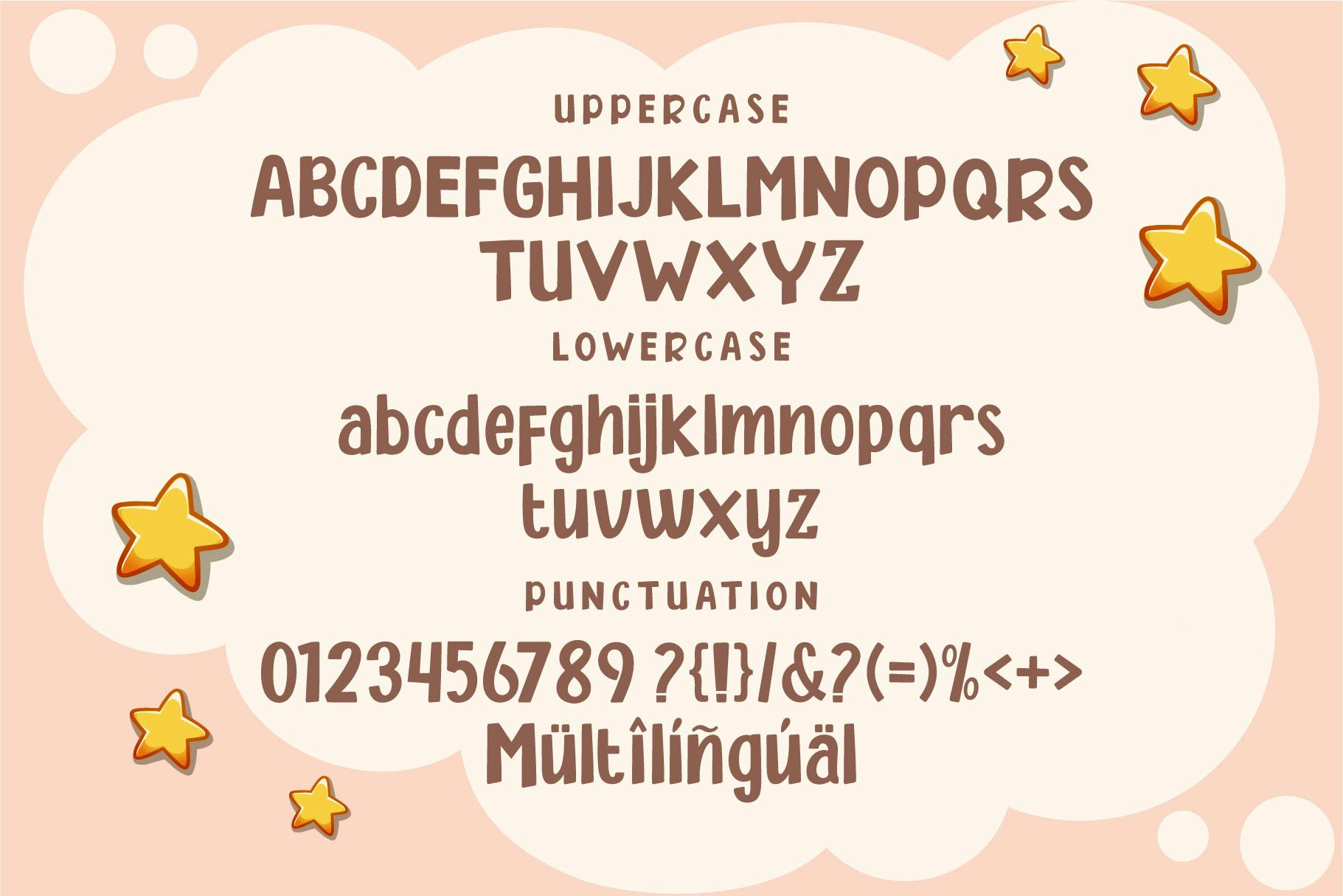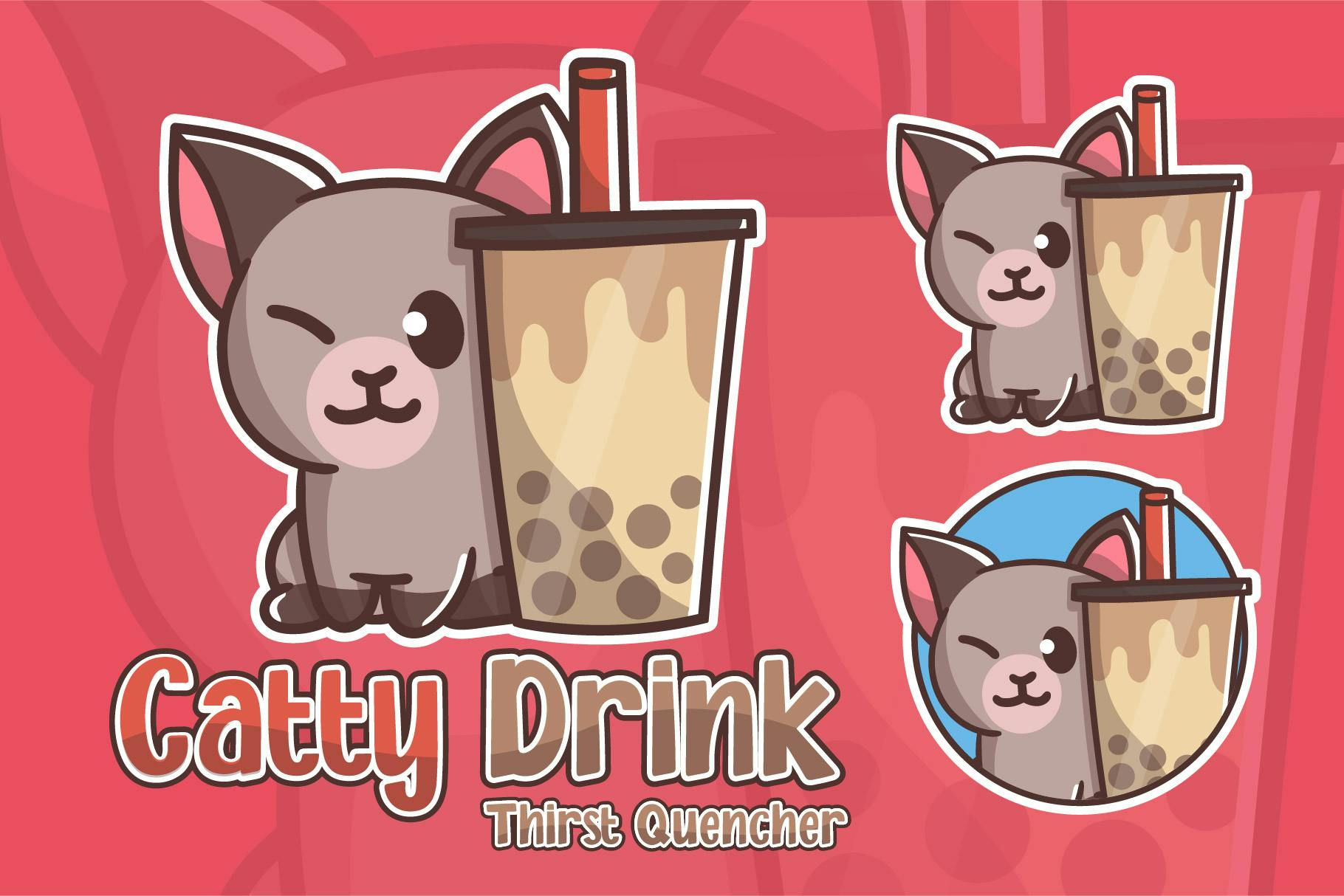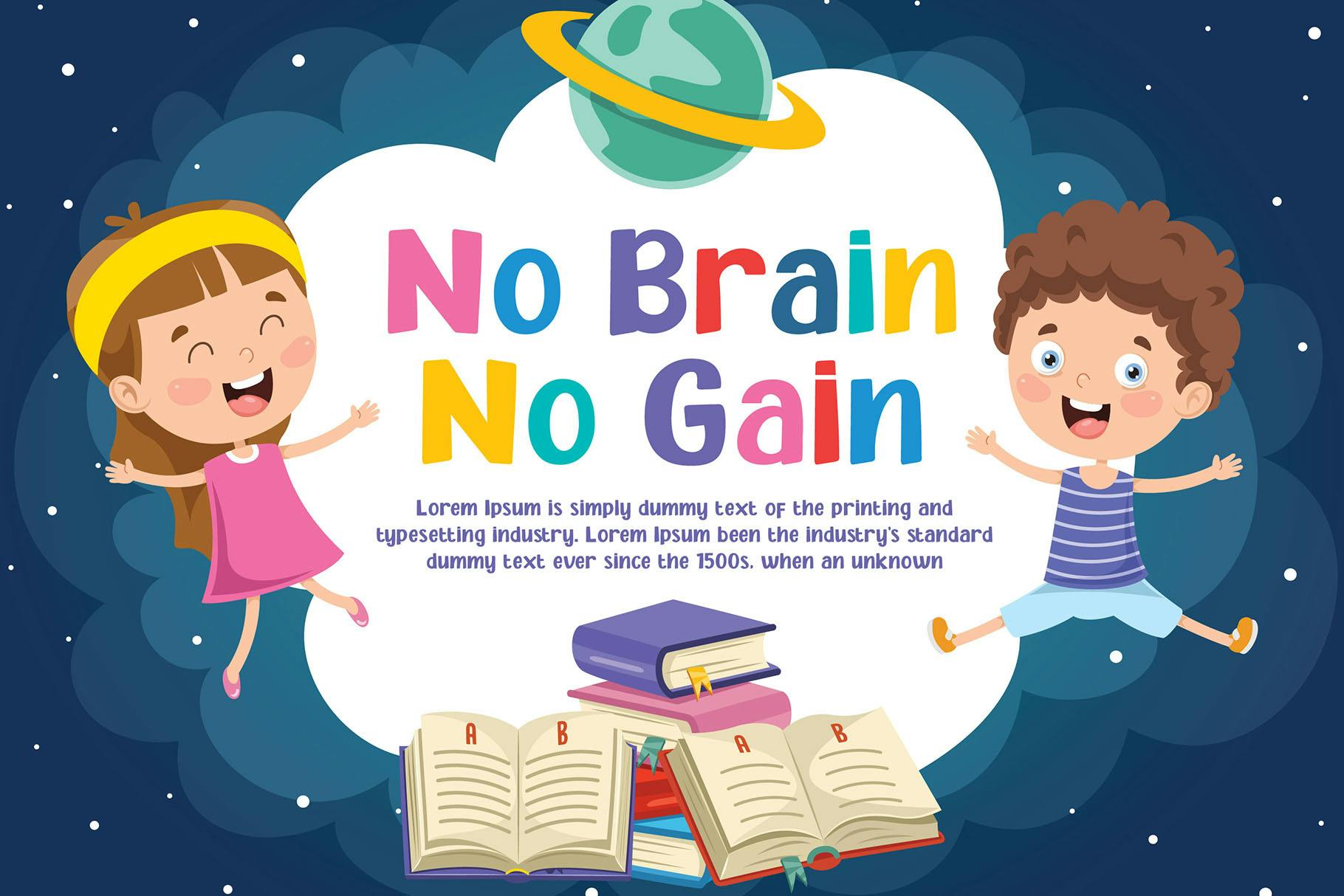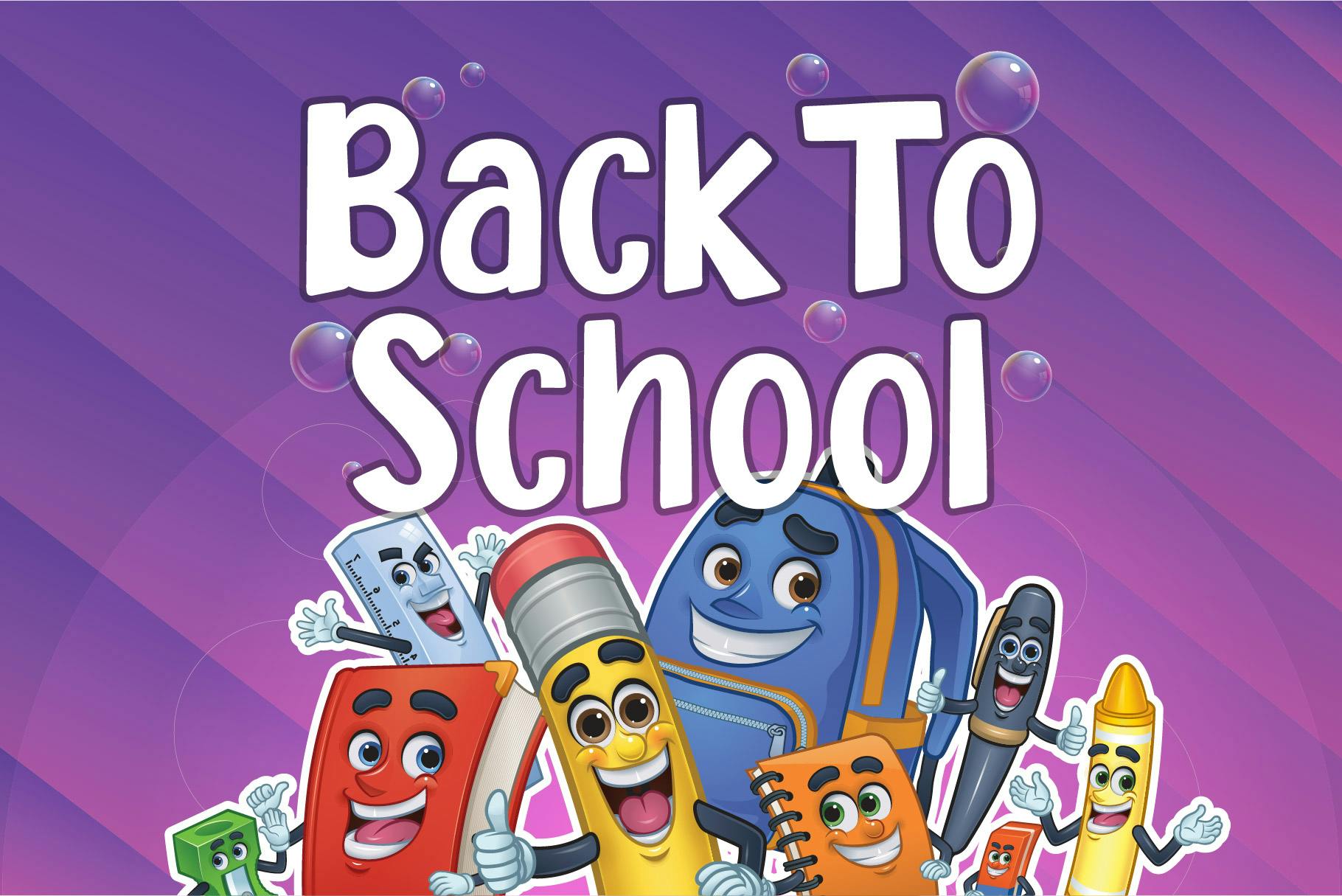
فونت نمایشی Ranked Hockey یک فونت شیک و جذاب برای طراحیهای مختلف است. این فونت میتواند برای محصولاتی مانند صنایع دستی، بستهبندی محصولات، نقلقولها، طراحی محصولات، کاردستیها، برچسبها، عکاسی، واترمارکها، لوگوها و برندینگ مورد استفاده قرار گیرد.